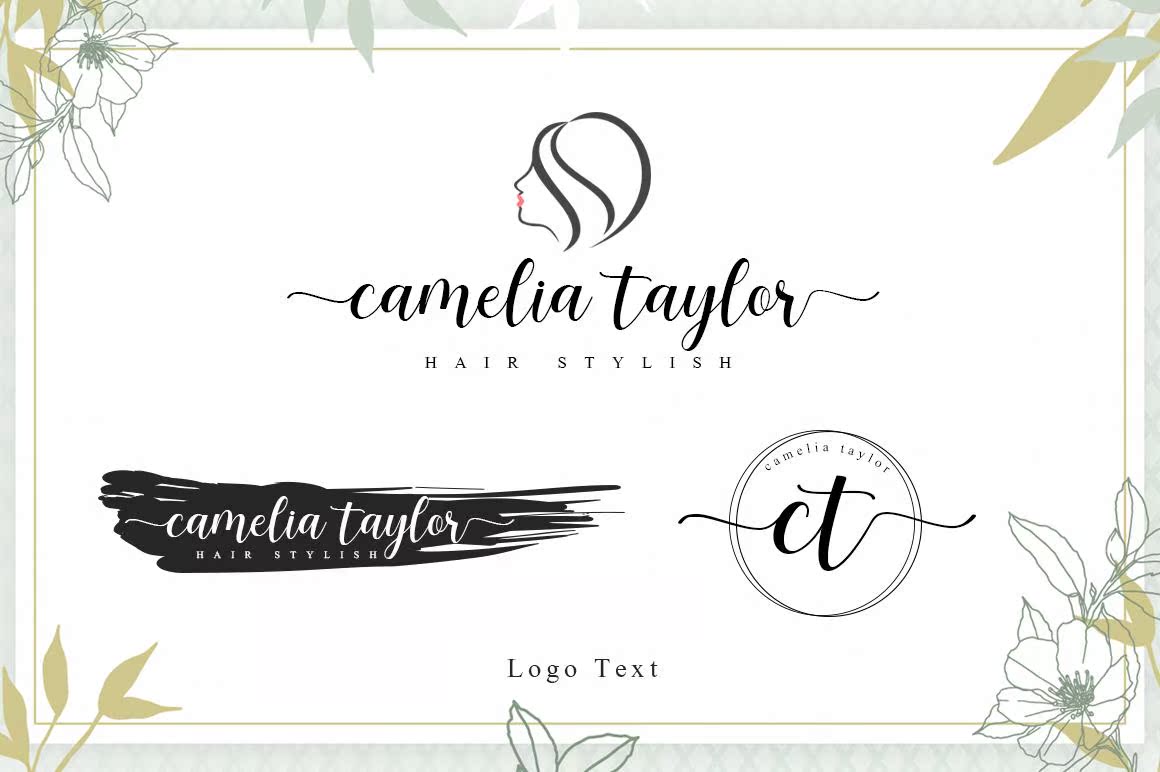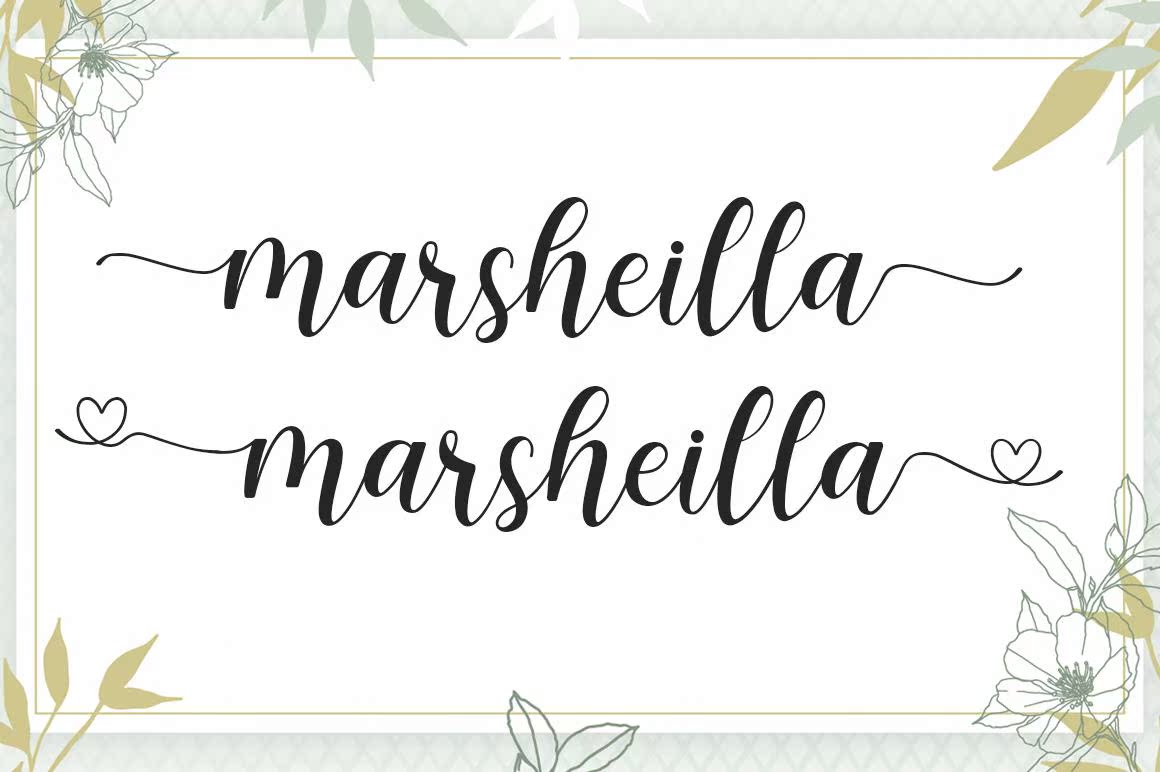
Marsheilla FontModern AlligraphyFonts,款式小巧、简洁,更适合搭配美丽的设计风格、婚礼、邀请函、品牌、女性标志、时尚、水印、,还有许多其他的……这款香水在一开始就有很多字母,有两种简单而美丽的变体。Marsheilla Font现代的彩色字体,样式小巧,或者是花哨、简单。更适合用于美丽的设计风格、婚礼、请柬、品牌、女性标志、时尚、水印、,还有很多其他的……这个方在开始的时候有很多字母,有两个简单而美丽的变体。